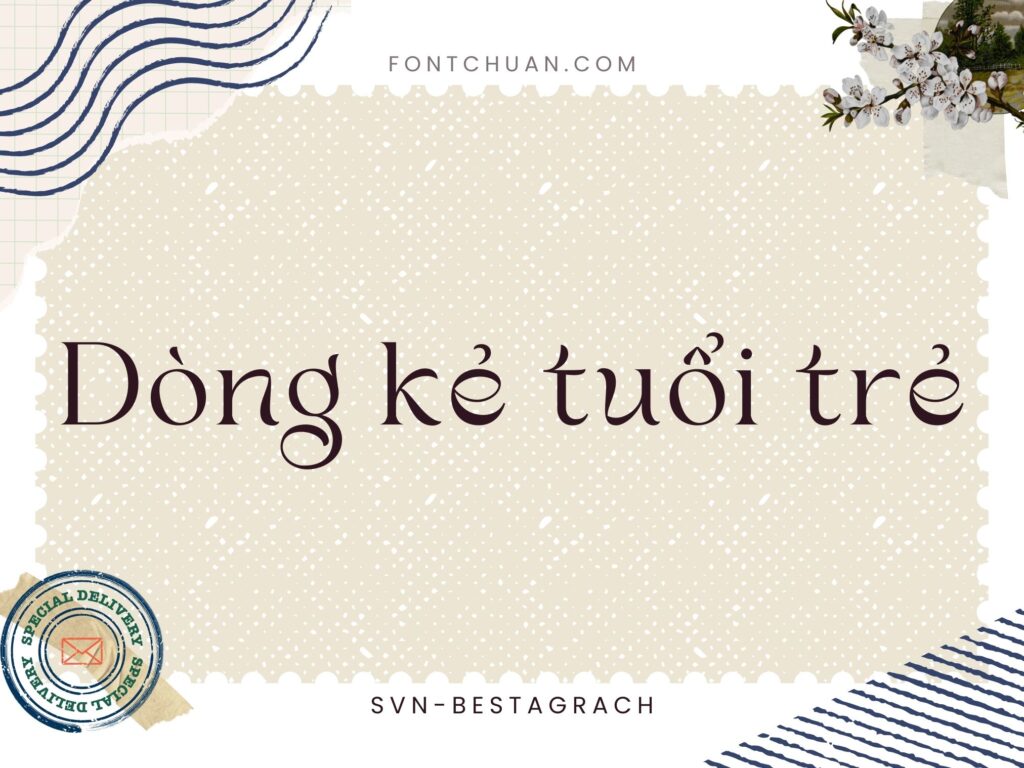
Font SVN Bestagrach Việt Hóa
Tác giả Font: Mokatype Studio
Font SVN-Bestagrach là phiên bản Việt hóa của kiểu chữ Bestagrach, được thực hiện bởi Styleno.1 Fonts. Bestagrach là một Font Serif thanh lịch với thiết kế chữ nối độc đáo, sử dụng các chữ ghép để liên kết các ký tự một cách trơn tru, tạo nên sự liền mạch và sáng tạo trong văn bản. Font này hoàn hảo để thêm nét độc đáo cho logo, chữ lồng hoặc trích dẫn.
SVN-Bestagrach lý tưởng cho các dự án thiết kế yêu cầu sự tinh tế và sáng tạo, như thiết kế logo, tiêu đề, bao bì sản phẩm và các ấn phẩm quảng cáo. Các ngành nghề như quảng cáo, thiệp cưới và ẩm thực có thể tận dụng font này để tạo điểm nhấn trong thiết kế. Ngoài ra, font cũng thích hợp cho các sự kiện như Tết, Valentine, Sinh nhật và các lễ hội khác.